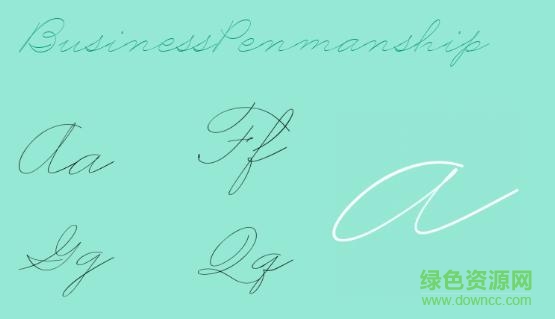
businesspenmanship字體又叫商務(wù)草書,是一款非常具有觀賞性英文手寫字體,結(jié)構(gòu)偏圓,線條流暢灑脫,藝術(shù)性強(qiáng),喜歡花體字體的朋友快來本站免費下載吧!
BP的難度較大,很多人認(rèn)為BP是國產(chǎn)圓體,這個當(dāng)然是錯的離譜的,國產(chǎn)圓體和BP的藝術(shù)層面不在一個級別,書寫難度更不在一個級別,如果說BP算是一種書法的話,國產(chǎn)圓體壓根就不是,BP有很高的藝術(shù)欣賞價值,二者在字形上的轉(zhuǎn)角,連筆,字形等諸多細(xì)節(jié)都有很大區(qū)別,切勿將二者相提并論。